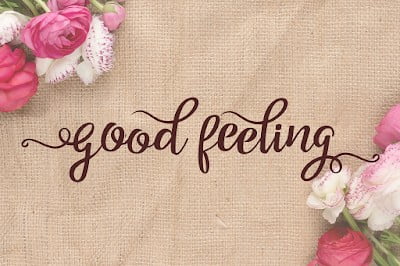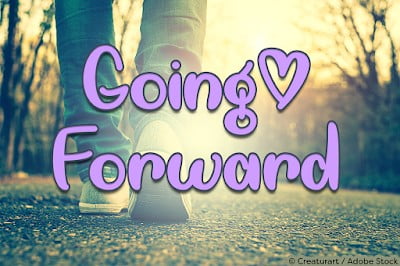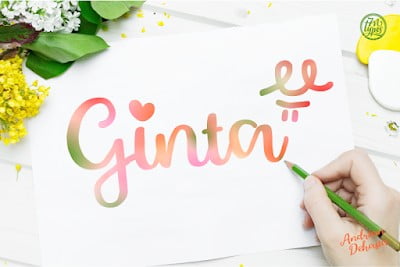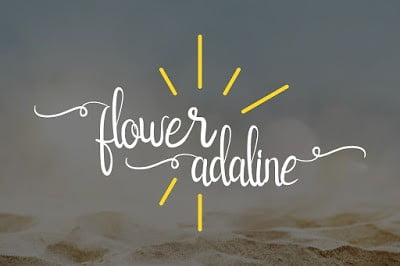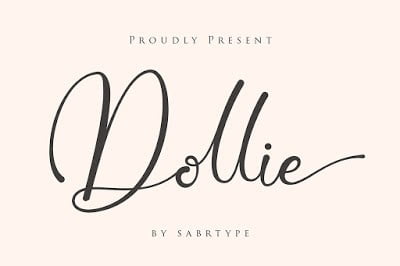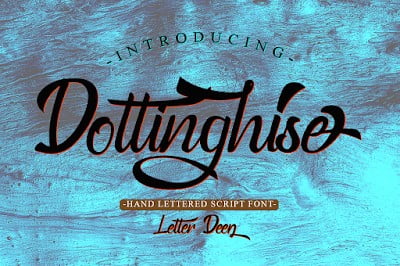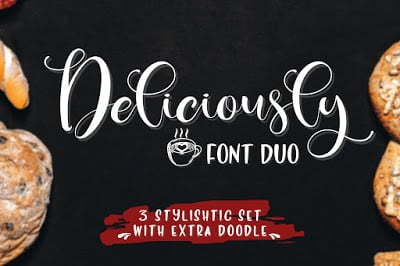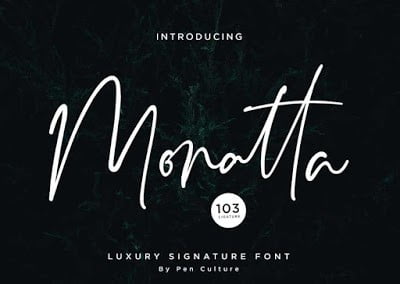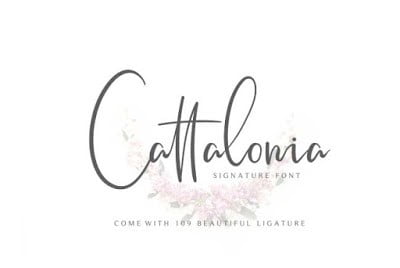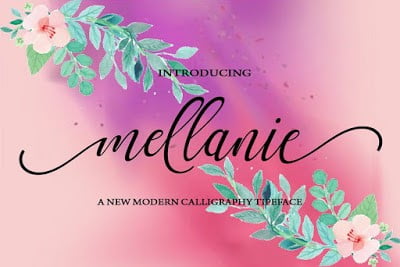
35+ Download Font Tulisan Tangan
37+ Download Font Tulisan Tangan Gratis 2020
37+ Download Font Tulisan Tangan Gratis Terbaik 2020 – Membuat sebuah desain dengan menampilkan coretan, pastinya harus mempunyai kreatifitas unik. Bahkan, ada banyak sekali pilihan motif-motifnya yang bisa Anda unduh sepuasnya. Maka dari itu, cobalah mengunduh font tulisan tangan gratis pada internet.
Apa Itu Font Tulisan Tangan atau Handwritten?
Font handwritten merupakan salah satu dari berbagai gaya tulis untuk pengaplikasian pada karya digital. Seolah-olah bentuk motifnya itu seperti tulisan tangan orang, terkadang juga menyerupai desan kaligrafi. Dengan demikian, dapat memberikan kesan santai dan casual pada desain.
Tulisan pada font ini identik dengan model tulisan tangan Latin. Selain itu, juga memiliki bermacam-macam bentuk, seperti goresan menggunakan spidol atau kuas. Ukuran hurufnya juga ada yang tebal, tipis, miring, tegak, agak kasar pada tepi dan lain sebagainya.
Ciri khas dari model tulisan tangan atau handwritten ini adalah adanya penggabungan antara huruf satu dengan yang lainnya, font seperti ini menunjukkan brand beauty, Vintage, Retro. Tentunya akan memberikan kesan keunikan pada karya.
Penggunaan Font Tulisan Tangan
Penggunaan font tulisan tangan atau handwritten ini adalah sesebuah cara yang baik dalam menambahkan karakter pada desain. Motif jenis ini betul-betul seperti goresan tangan orang, namun ada juga dalam pembuatannya menggunakan cara sketsa terlebih dahulu dan menscan ke aplikasi.
Terdapat berbagai macam karakter pada model tulisan tangan ini, ada kalanya bisa terbaca dengan sangat bersih dan jelas. Namun ada pula font yang sulit untuk membacanya, karena bisa jadi adanya pengaruh mood desainer ketika menciptakannya.
Semakin menarik suatu font, maka semakin cantik pula tampilan desain. Model tulisan tangan ini pun memang menambahkan tingkat pesona tertentu yang berbeda dengan bentuk lainnya. Karena banyak terdapat pilihan goresan-goresan motif unik, maka gunakanlah gaya tulis ini untuk desainer.
Macam-Macam Font Tulisan Tangan Gratis
Apa manfaatnya mendownload font tulisan tangan ini?
Dengan font tulisan tangan gratis ini, maka tampilan desain akan lebih menarik dan terlihat unik. Terdapat banyak sekali model-model dari dont tulisan tangan ini. Berikut adalah penjelasannya.
1. Cervanttis
Cervanttis
Font Cervanttis
Pembuat tulisan unik ini adalah Mats-Peter Forss. Untuk menampilkan nuansa tulisan tangan, penggunaan coretan pada logo, branding, iklan, dan postingan sosial, maka cocok sekali menggunakan jenis font gratis satu ini tanpa adanya pembayaran sepeserpun. Download Font Cervanttis
2. Timothy
timothy
Font Timothy
Untuk pilihan selanjutnya adalah Font Timothy. Terciptanya tulisan unik ini sebernarnya terinspirasi oleh desainer Timothy Goodman. Desain coretannya menggunakan huruf besar kapital dengan sentuhan khas tangan. Mendownloadnya pun gratis, namun Anda perlu memberikan alamat E-Mail. Download Font Timothy
3. Kavivanar
Kavivanar
Font Kavivanar
Pilihan selanjutnya adalah Font Kavivanar buatan dari Tharique Azeez. Awalmula mendapatkan inspirasi yaitu dari tulisan tangan Tamal yang khas berbentuk miring. Selain itu, coretan ini juga termasuk bentuk huruf Latin. Download Font Kavivanar
4. Thomato Soup
Tomato Soup
Font Tomato Soup
Pernahkah Anda pergi menemui dokter untuk berobat? Jika pernah pasti akan memberikan tulisan resep pada selembar kertas. Namun, terkadang hanya ada coretan yang sulit untuk membacanya. Bila ingin menggunakan bentuk model handwritting seperti itu, maka gunakanlah Font ini. Download Font Thomato Soup
5. Ambarella
Ambrella
Font Ambrella
Untuk mampilkan coretan tangan yang indah, maka bisa menggunakan Font Ambarella ini. Pembuat tulisan unik ini adalah Pole Studio. Motif desainnya menggunakan gaya kaligrafi modern dengan mencangkup berbagai swash, alternatif dan gaya ala Eropa Barat. Download Font Ambarella
6. Nickainley
Nickainley
Font Nickainley
Termasuk lagi tulisan tangan gratis favorit adalah Font Nickainley. Disuguhkan Skrip Monoline dengan penambahan nuansa klasik dan vintage, terdapat pula berbagai karakter huruf besar kecil, angka seta tanda baca. Pembuatnya adalah Seniors Studio, cocok untuk desain logo, T-shirt, kop surat, signage. Download Font Nickainley
7. Shadows into Light
Shadow Into Ligh
Font Shadow Into Ligh
Tulisan tangan tak kalah populer lagi adalah Shadows into Light. Pembuatnya yaitu karya desainer font Kimberly Geswein. Jenis ini cocok sebagai tambahan setuhan pribadi pada proyek, sebab memiliki tepi bulat berkarakter rapi dan bersih. Download Font Shadow Into Light
8. Cute Punk
Cute Punk
Font Cute Punk
Untuk menampilkan sensasi bersemangat, awet mudah dan sepenuhnya modern pada desain, maka cobalah menggunakan font cute punk dengan nuansa yang hampir geometris pada bentuk motifnya. Pembuat tulisan tangan ini adalah Flou, seorang desainer serta ilustrator dari Bratislava, Slovakia. Download Font Cute Punk